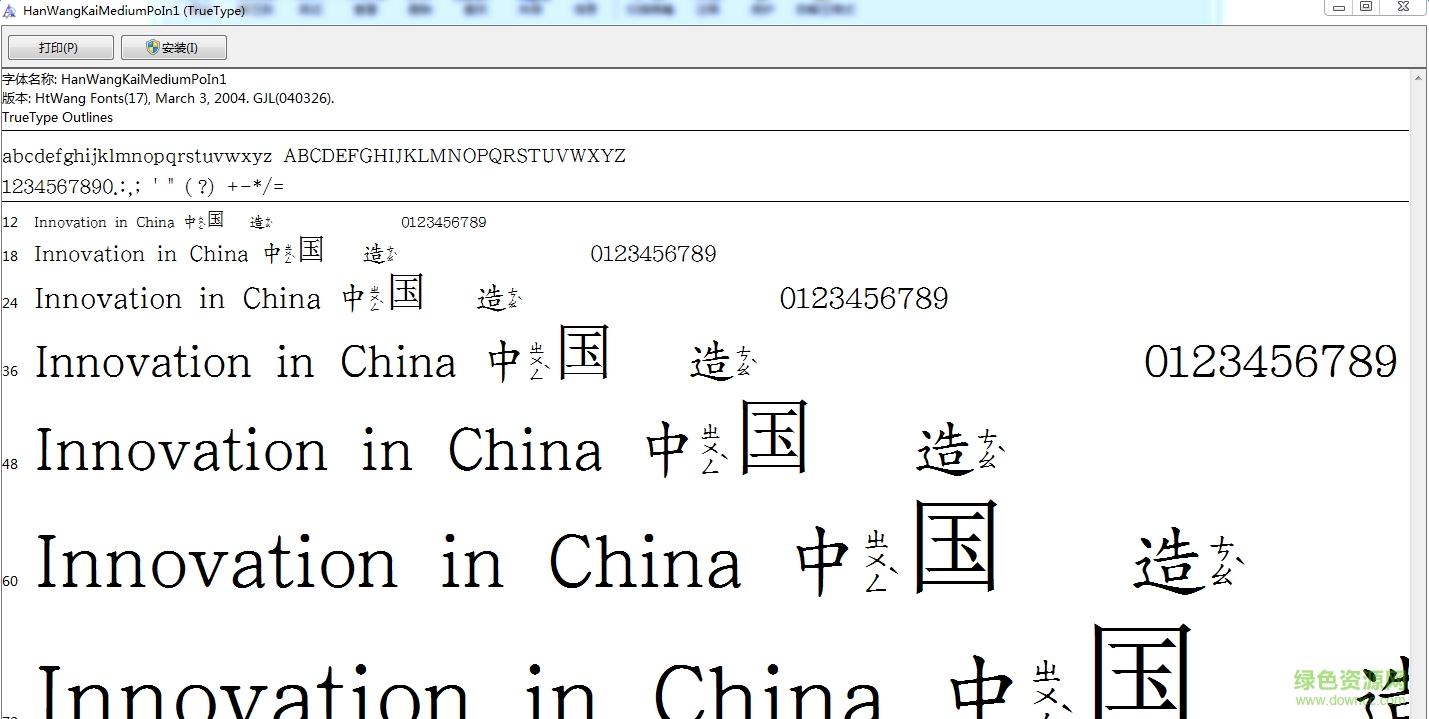
王漢宗中楷體破音一字體和同系列的其他字體外形類似,也是在印刷、廣告設(shè)計(jì)行業(yè)使用的比較普遍!這款資源可以用來(lái)輸入漢字、英文、數(shù)字內(nèi)容。喜歡的用戶歡迎在綠色資源網(wǎng)下載。
王漢宗中楷體破音一是一款王漢宗類中楷字體,字體效果比較正規(guī)!